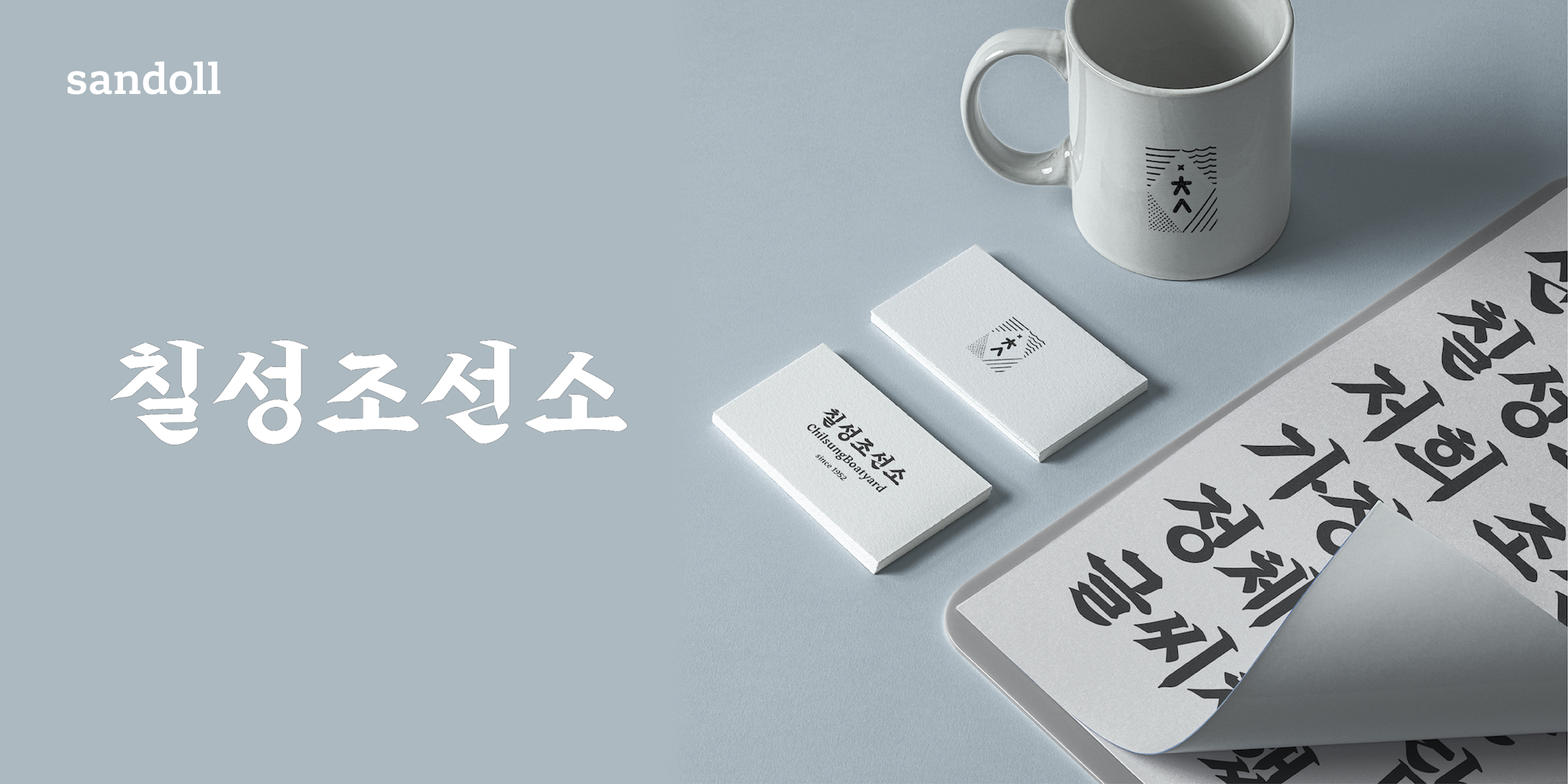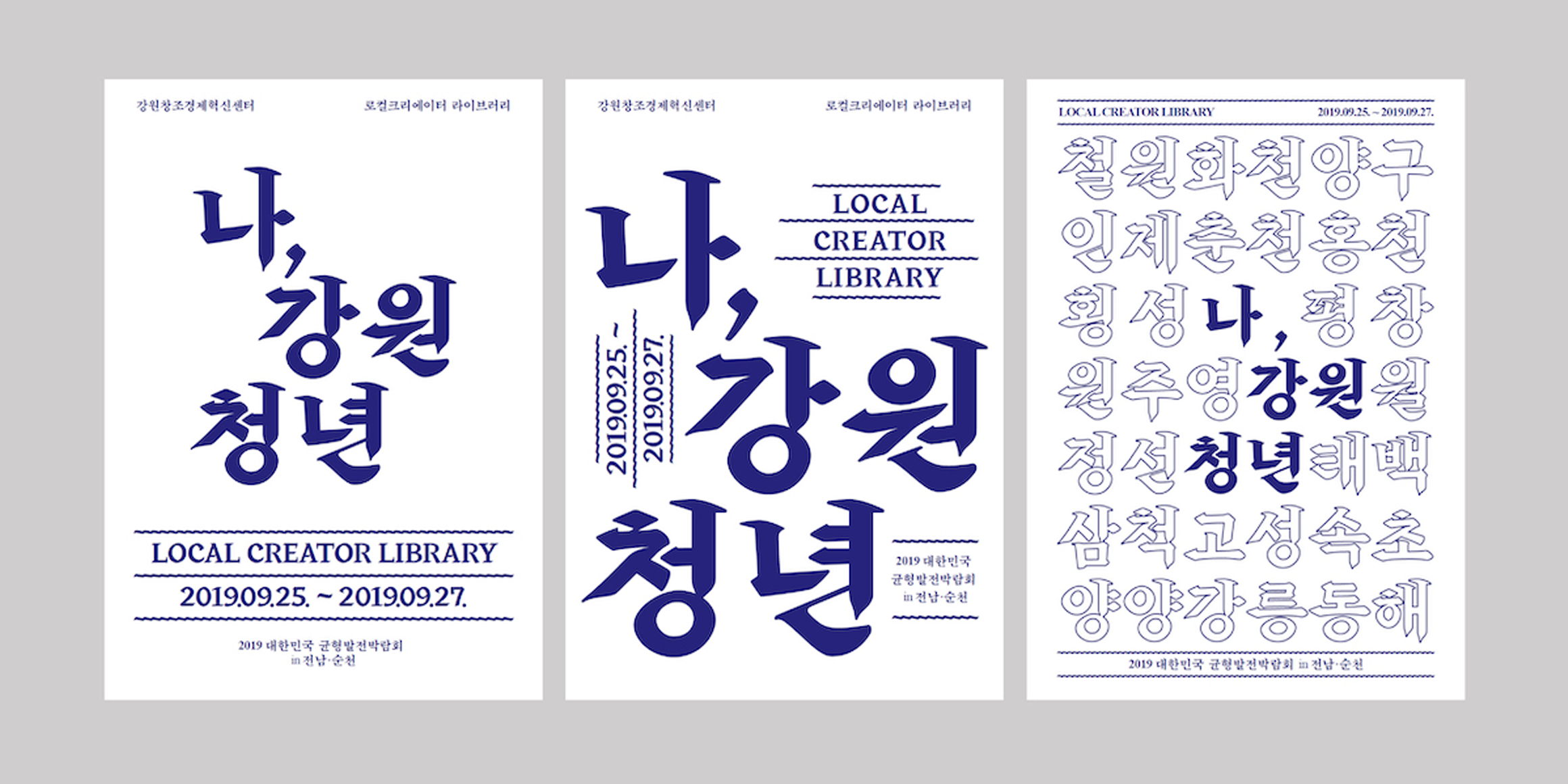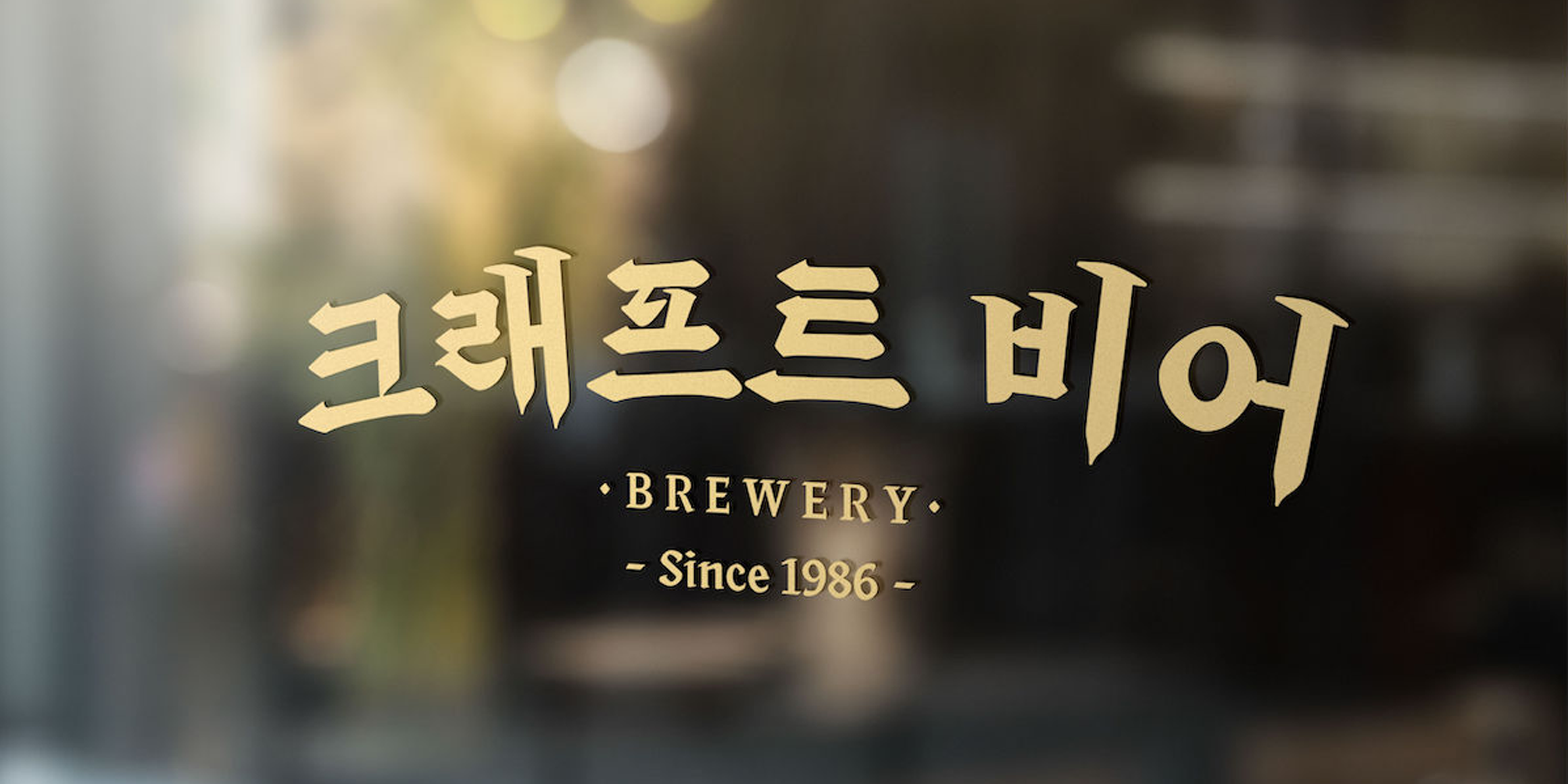
Sandoll 칠성조선소
산돌 칠성조선소는 강원도 속초에 위치한 옛 조선소이자, 현재는 복합문화공간으로 새롭게 탄생한 <칠성조선소>의 손글씨 원도를 바탕으로 제작된 폰트입니다.
특유의 기울기로 인해 전반적인 폰트의 외형이 마름모꼴처럼 보이는 특징이 있으며, 원도에 담겨있는 붓끝의 움직임, 흔적 등을 재해석해 현대적인 미감으로 새롭게 다듬고 정제해 디자인했습니다.
제목에 활용하기 좋으며, 24포인트 이상의 크기로 사용할 때 폰트가 갖고 있는 본연의 멋과 개성을 온전히 전달할 수 있습니다.
• 2019
• 강주연 진유성
• 한글 2,780자 / 라틴 95자 / / 약물 410자 / / / 추가글립(딩벳) 5자
• Sandoll 칠성조선소 / Sandoll ChilsungBoatyard